什么字体更适合程序员?
Fira Code – 带有连字的免费等宽字体
Nerd Fonts – 修补了具有大量字形(图标)的开发人员目标字体。特别是从流行的“标志性字体”中添加大量额外的字形,例如 Font Awesome、Devicons、Octicons等。3,600 多个图标,50 多种修补字体,如 Hack、Source Code Pro 等。
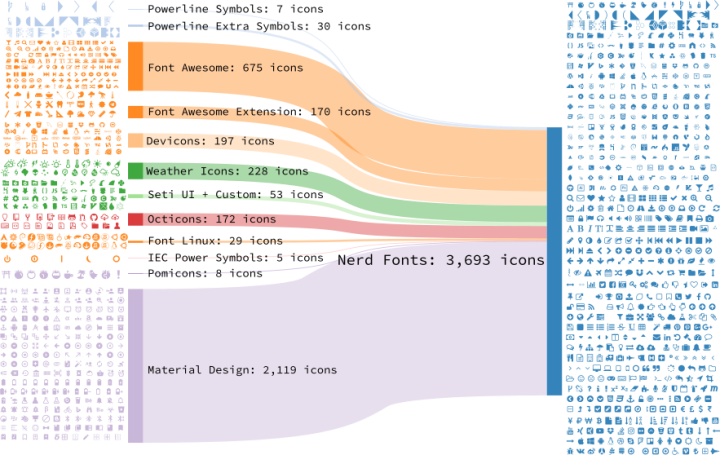
Operator Mono – 对编码友好的字体,Operator Mono 字体本身并不支持类似于 Fira Code 的连字,但是在社区有个工具专门针对 Operator Mono 字体做连字处理。
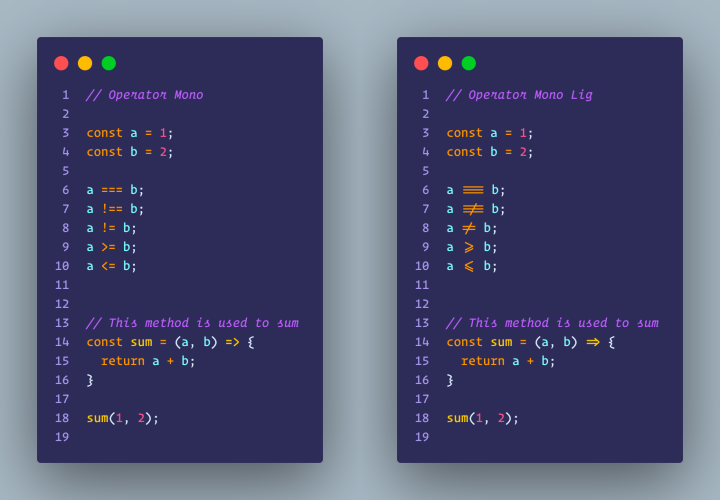
制作连字的 Operator Mono 字体
字体效果预览